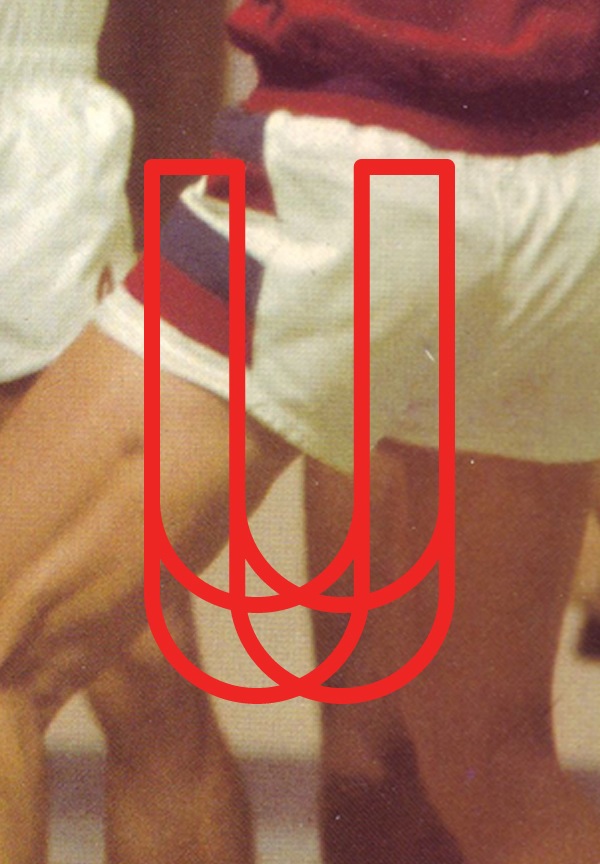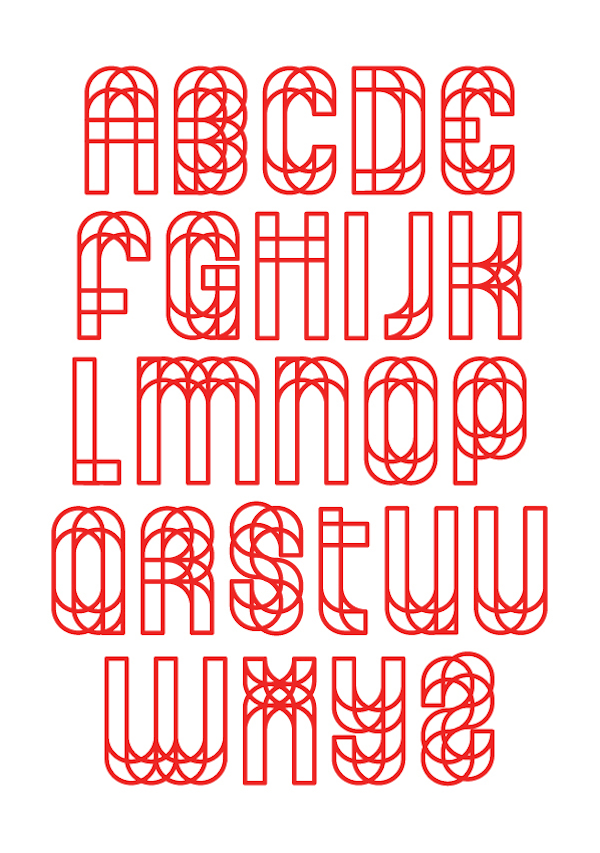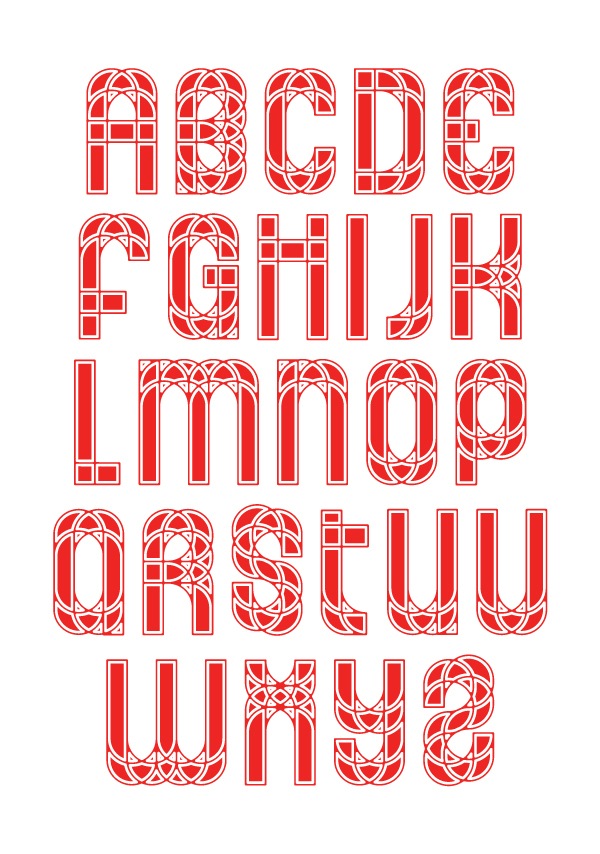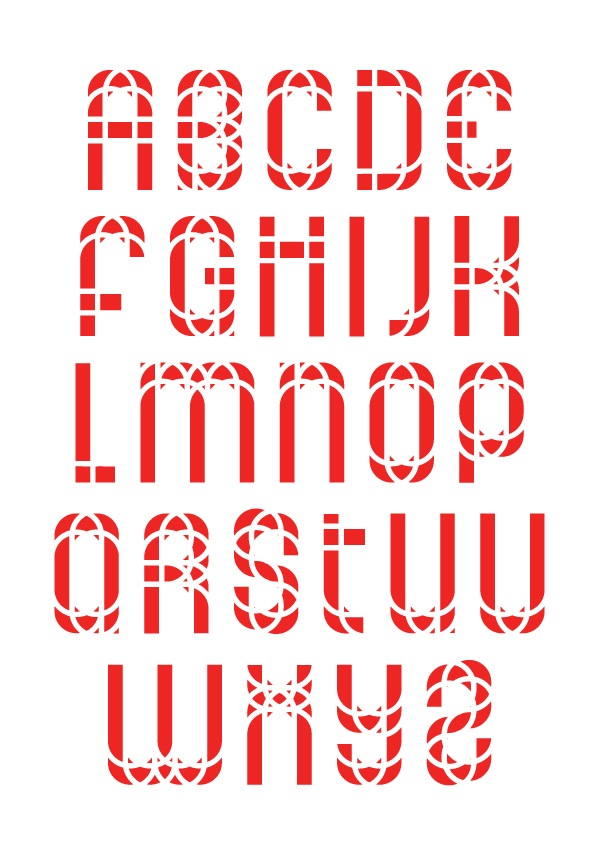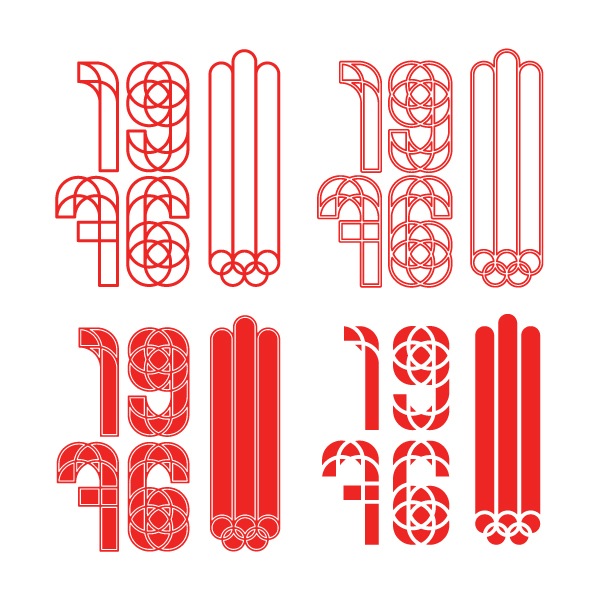
El canadiense Patrick Seymour trabaja en diferentes campos de la comunicación visual, incluyendo el diseño gráfico, el arte digital, la Ilustración y el diseño de tipografías. Inspirado en los Juegos Olímpicos de Montreal, ha creado 1976, una fuente que homenajea el logotipo que Georges Huel y Pierre-Yves Pelletier diseñaron para el evento; un verdadero icono del diseño canadiense. Además, para crear las múltiples versiones de los carcacteres que completan su diseño, Patrick Seymour se ha inspirado en diferentes imágenes de las competiciones de los juegos.